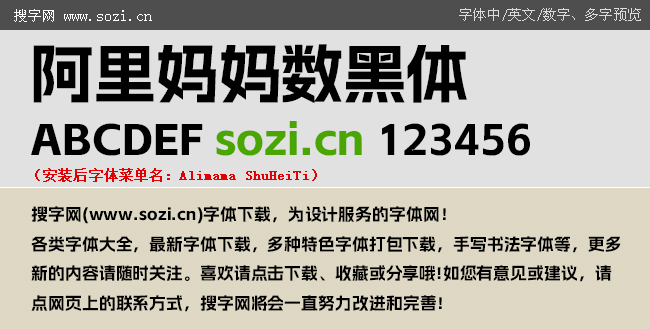
阿里媽媽數黑體
搜字網給大家提供一款阿里媽媽數黑體中文字體下載,阿里媽媽數黑體是一款AI字體產品,由阿里媽媽·智造字自產自研打造,數黑體字型飽滿、體態中正,布白極具現代韻律,落筆厚實而簡練;字里行間流露出先鋒、時尚、醒目的視覺感受。適用于電商、廣告、品牌形象、推廣物料等場景。 數黑體是永久免費正版商用字體,將對全社會免費開放使用。